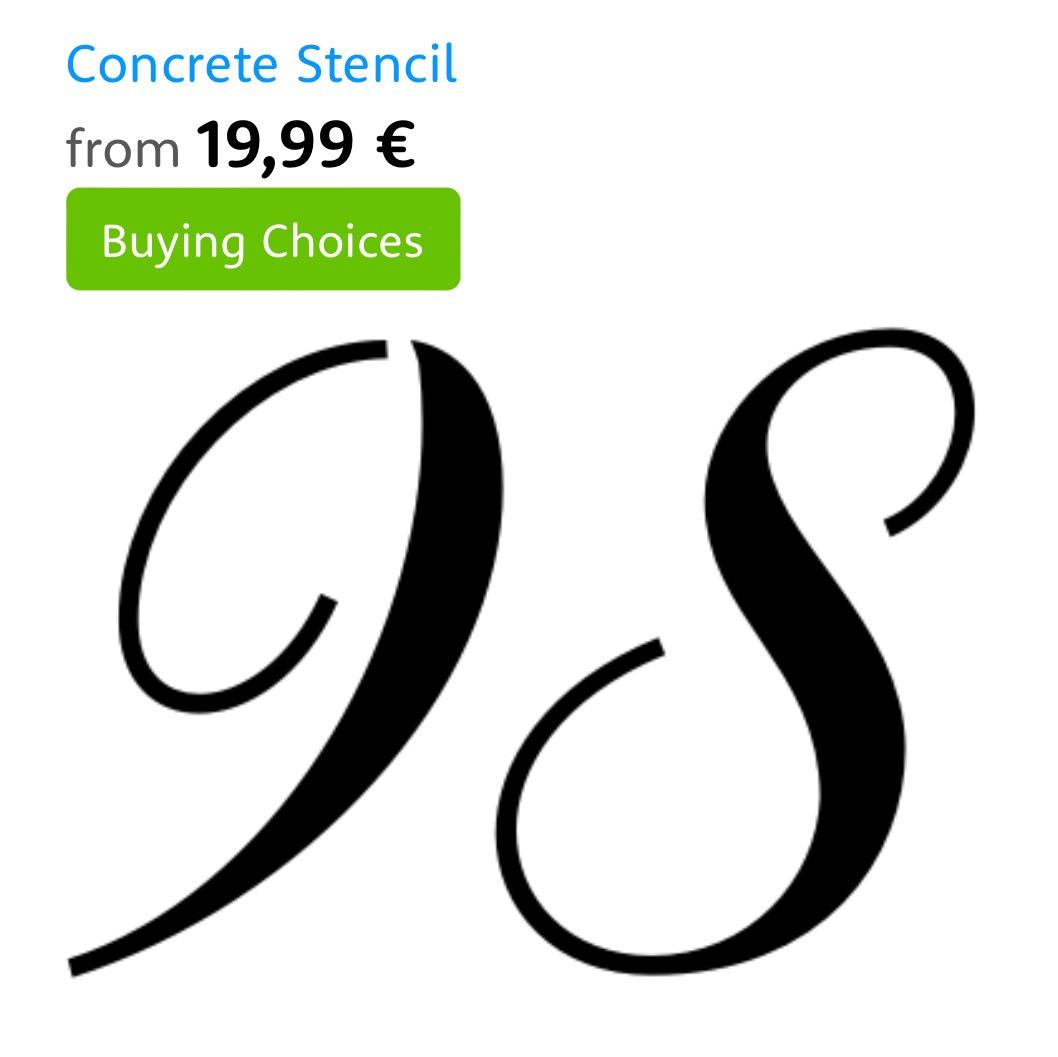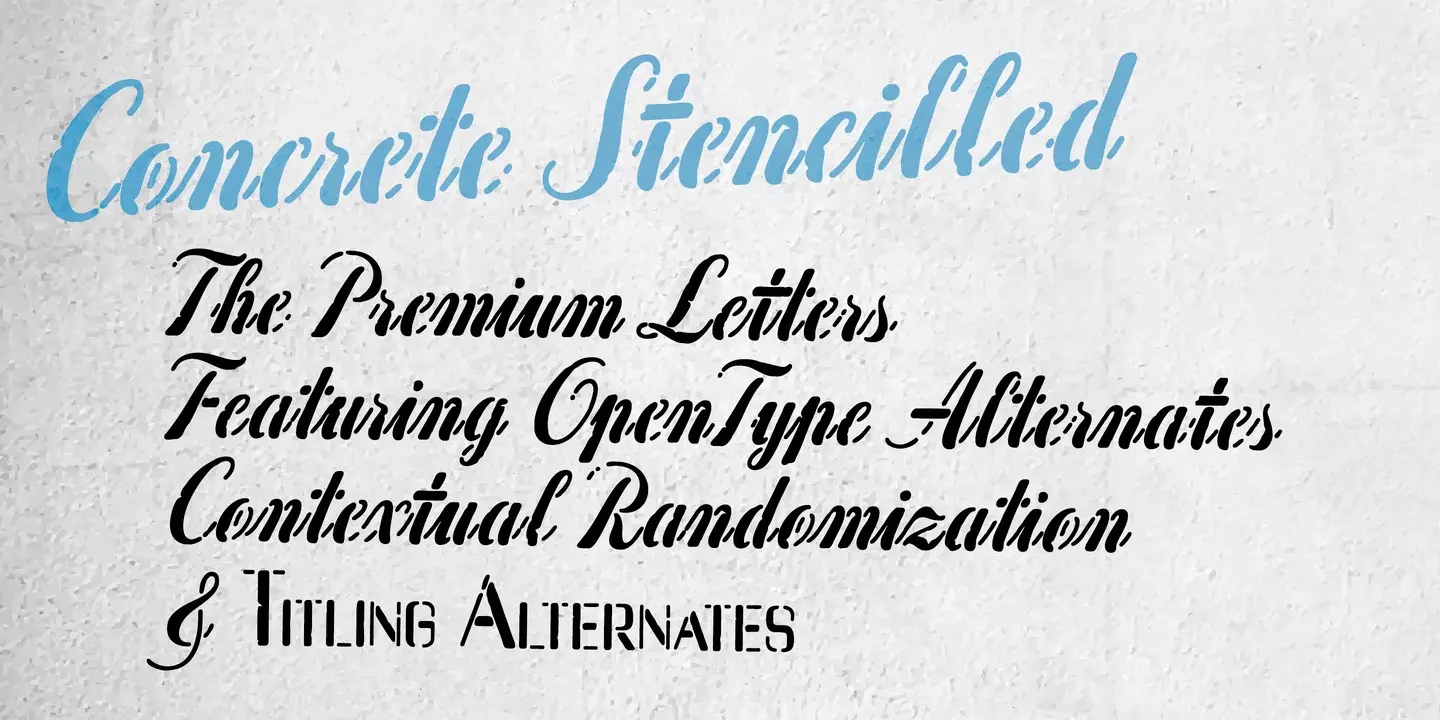
Schablonenschriften in Handschriftlichen Stiel mit Zahlen
Leider habe ich auf meiner Suche nach Schablonenschriften nichts gefunden was mir gefällt. Immer wieder finde ich die Militärschriften , jedoch nichts was einen etwas geschwungenen handschriftlichen Karakter hat.
Wer hat einen Tipp für mich oder einen Link zum runterladen der Schrift. Ich bin auch gerne bereit eine Schrift zu kaufen.
Hallo @Schwarzrock, hier sind beispielhaft drei Downloadlinks zu zwar nicht handschriftlichen, doch eleganten und entschieden unmilitärischen Schablonenschriften:
Laima (von Bogidar Mascareñas für Typetogether)
Pensum Stencil (von Nils Thomsen für TypeMates)
Dala Floda (von Paul Barnes und Ilya Ruderman für Commercial Type)
Vielleicht findest du auch auf der entsprechenden Fontliste weitere Anregungen.
Mir ist auch noch nicht ganz klar, was Du genau mit „handschriftlich“ meinst. Vielleicht wäre es eine Idee, dass Du uns mal einen entsprechenden Font ohne Stencil-Eigenschaften zeigst, damit wir Dir dann gezielter helfen können?
Ich suche etwas in der Art oder Richtung French Script MT.  Die Schrift soll ausgeschnitten werden und dennoch einen freundlichen Eindruck hinterlassen und nicht wie die Armee Klasse wirken. Es geht dabei hauptsächlich um die Zahlen wie in meinem Beispiel im Anhang. Die 98 soll ausgeschnitten werden.
Oh ja, das hilft mir schon weiter, das ist die Richtung die ich suche.
Dann werde ich dort weiter graben und sicherlich das richtige finden.
Stencilschriften, die nicht militärisch anmuten, findest du auch in diesem Thread: